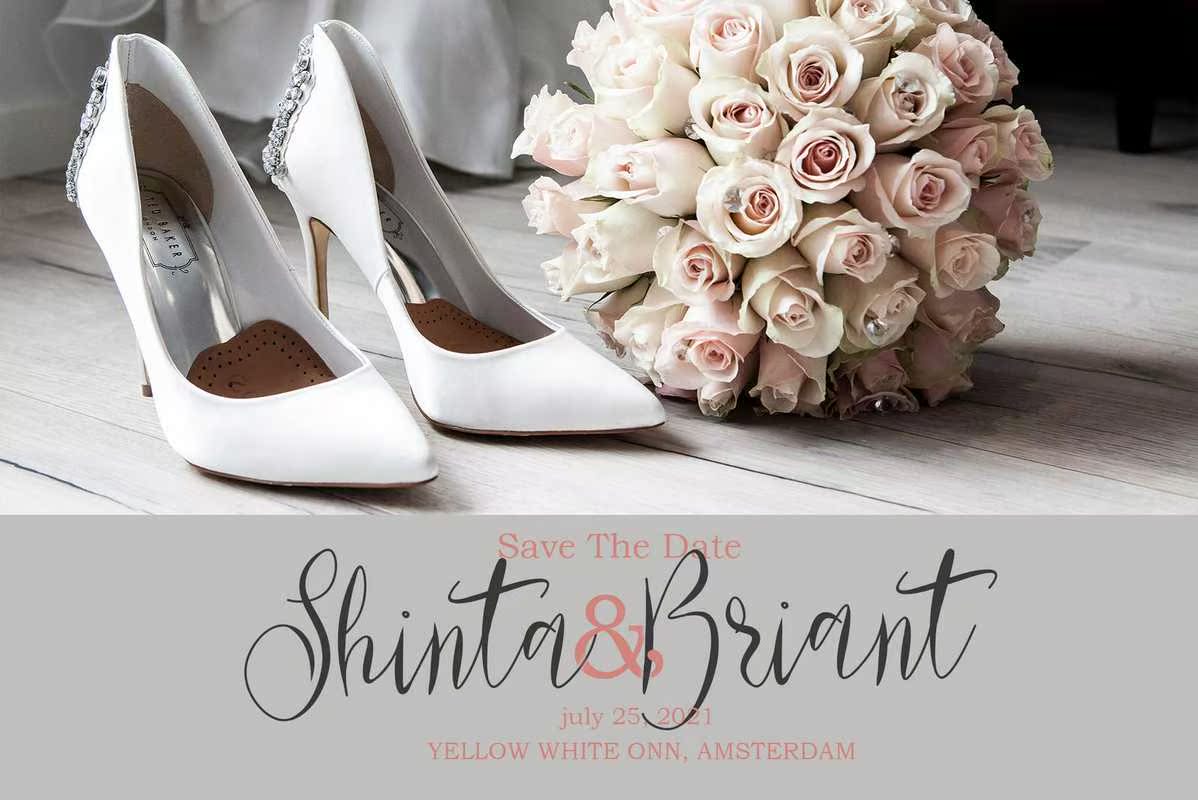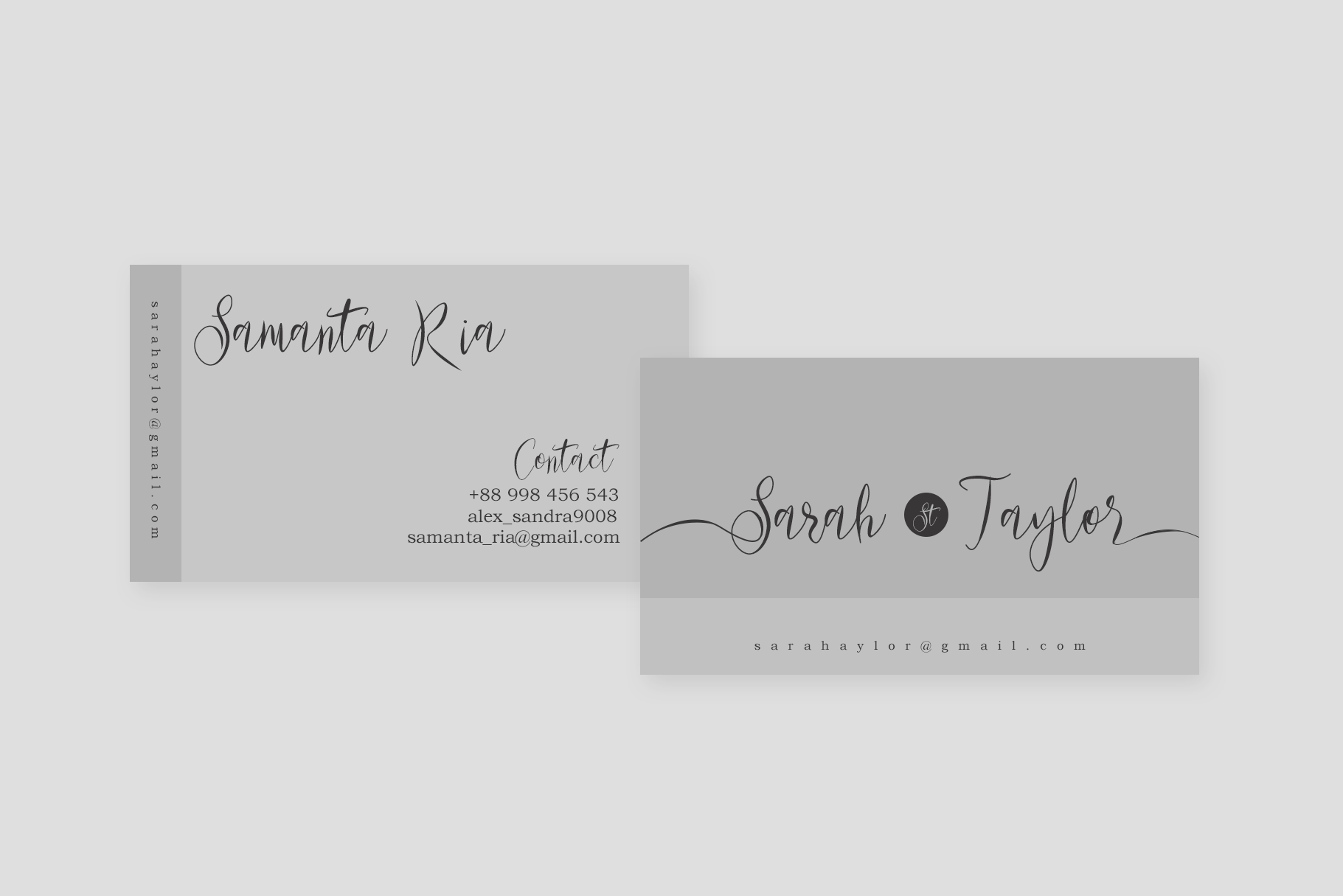
Paris Hillton Information with ScriptStyles。适合您项目的文字和数字集合非常适合于标识、品牌设计、标识设计、数字刻字艺术、T恤/服装、海报、杂志、标志、广告设计和任何设计需求。Paris Hillton Information with ScriptStyles。适合您项目的文字和数字集合非常适合于标识、品牌设计,标志设计、数字文字艺术、T恤/服装、海报、杂志、标志、广告设计和任何设计需求。